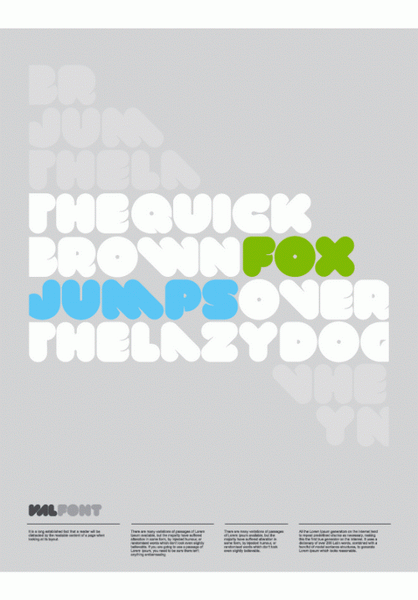
VAL é uma fonte gratuita com um estilo diferente para maiúsculas e minúsculas que pode ajudar bastante em algums projetos.fontfabric.com via Free font VAL™ on the Behance NetworkpreviousBreak&Assemblenextit’s Blue River Related Posts Encenando a Voz da Oração: Como a 2K/Denmark Cria os Livros Mais Bonitos do Mundo Nos bastidores da nova tipografia personalizada de Wallace & Gromit por Jamie Clarke Buchstabenmuseum em Berlim: O fechamento do único museu de letras da capital alemã Leave a ReplyYour email address will not be published. Required fields are marked *Name * Email * Website Comment * Δ This site uses Akismet to reduce spam. Learn how your comment data is processed.Tags:behanceDownloadfontefontesgratisgratuito